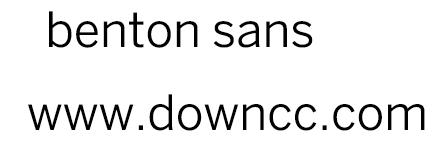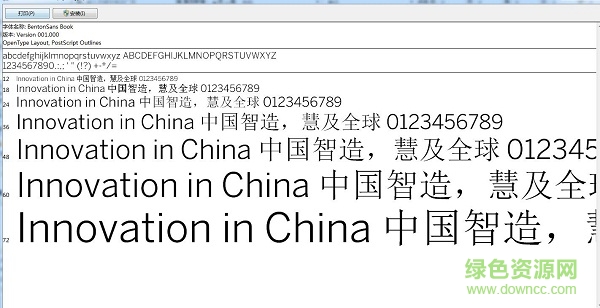
bentonsans-book字體
bentonsans 字體是一款不落俗套的無襯線字體,充滿干凈理性的氣息,安全實用,蘋果、微軟、三星等大品牌的logo標(biāo)志都是采用無襯線字體,需要的朋友快來下載吧!
無襯線字體的起源
第一款無襯線字體誕生于1816年,是由英國的威廉姆·卡斯隆創(chuàng)作的,但并沒有引起人們的注意。那時還是古典、優(yōu)雅的襯線字體的天下,新生的無襯線字體被看成為“丑八怪”,主要是畫廣告牌的師傅和石匠在使用。隨著工業(yè)化的展開,傳統(tǒng)、古典的襯線字體不僅顯得老套,而且日漸不能滿足廣告宣傳的繪制和做版需求。